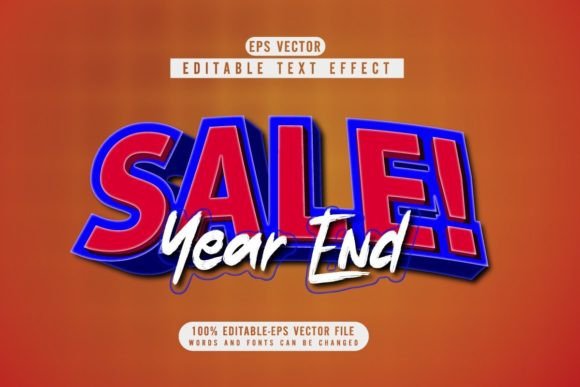
Editable Text Effect in Discount Sale St
Editable Text Effect in Discount Sale Stμ κ°μ κ³ νμ§ μμ°μ μ°Ύκ³ μλ€λ©΄ μ΄ ν리미μ ν¨ν€μ§λ μ°½μμ μΈ νλ‘μ νΈλ₯Ό μν νμμ μΈ μ νμ λλ€.